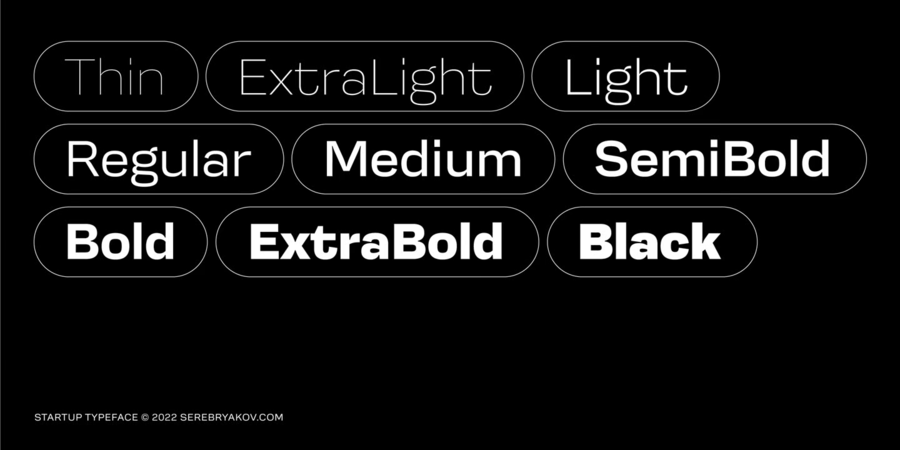
Стартап – це гарнітура у дев’яти накресленнях, яка поєднує в собі естетику старого гротеску та неогротеску. Шрифт створений спеціально для створення айдентики стартапів. Коли потрібно щось, що не кричить, але має індивідуальність. Дане шрифтове сімейство можна використовувати в дизайні логотипів, а також застосовувати в заголовках і другорядних текстах. Накреслення Startup Extra Light є безкоштовним для будь-якого комерційного та приватного використання. Шрифт розробив Денис Серебряков у 2022 році.
Асоціації з сімейством шрифтів StartupОсобистість і характер гарнітури:
інженерний, точний, логічний, рівний, міський, якісний, західний, сучасний, модний, холодний, тонкий, легкий, невагомий, прозорий, крихкий, футуристичний, дротяний, прохолодний, космічний, діловий, серйозний, стабільний, статичний, стійкий, глобалізований, глобалістічний, технічний, свіжий, ясний, чіткий, креслярський, формальний, зрозумілий, різкий, Простий, динамічний, впевнений, надійний, спортивний, важливий, переконливий, мотивуючий, твердий, солідний, сильний, залізний, сталевий, міцний, мужній, потужний, авторитетний, помітний, важкий, індустріальний, техногенний, крутий, яскравий, активний, гострий, суворий, амбітний, значний, кондовий, добротний, щільний, гучний, сміливий, брутальний, урбаністичний, самостійний, рішучий, енергійний, іронічний, претензійний, здоровий, грубий
прилад, гаджет, девайс, дизайн, креслення, технології, інновації, Місто, фантастика, космос, техніка, наука, інтернет, мобільний зв'язок, айтішник, айті, IT, інженер, архітектура, конструктор, медицина, суспільство, коворкінг, бізнес, транспорт, аеропорт, метро, ліки, фінанси, астрономія, хімія, фізика, комп'ютерна гра, авто, автомобіль, паливо, торгівля, магазин, реклама, поліція, аптека, залізо, комп'ютер, Локдаун, логістика, верстат, машинобудування, промисловість, енергетика, електростанція, спорт, інструмент, мотор, двигун, телебачення, взуття, завод, металургія, урбаністика, джинси Гарнітура має ознаки стилів: